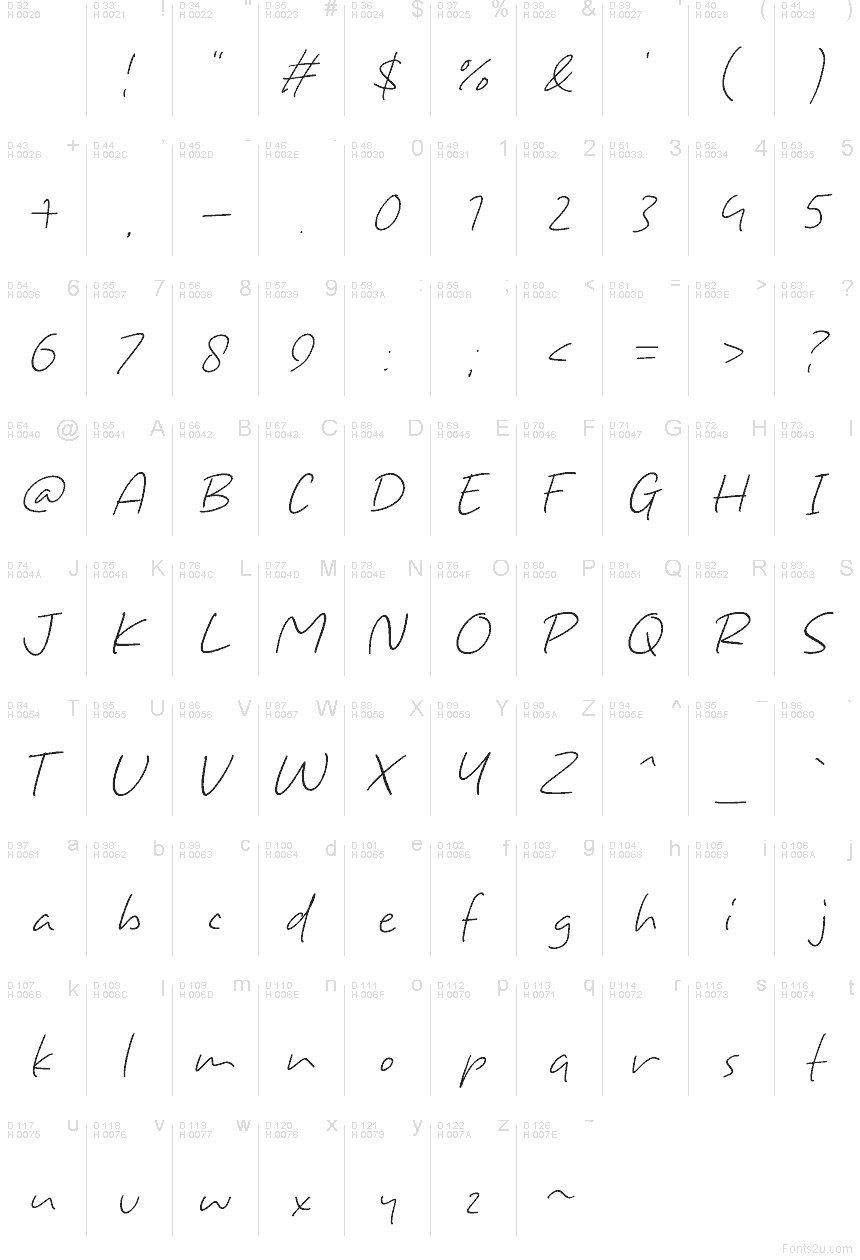
Standing Handwriting
Standing Handwriting от MJType — это бесплатный рукописный шрифт с современным и непринужденным характером. Буквы выглядят как легкие наброски, стоят прямо, обладают длинными, воздушными штрихами и свободным ритмом, напоминающим скорее быстрые заметки, чем отточенную каллиграфию.
Он органично вписывается в брендинг, упаковку, посты в соцсетях, цитаты, заголовки в дневниковом стиле и короткие фразы на плакатах, где бесплатный шрифт должен выглядеть лично, не перегружая дизайн. Используйте его для заголовков, имен или коротких надписей — свободные соединения и высокие, летящие штрихи придают даже паре слов человечный и спонтанный тон.